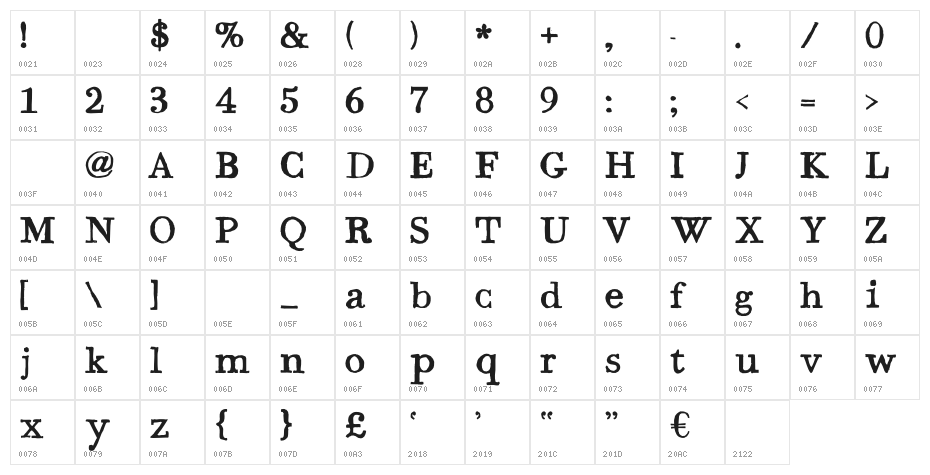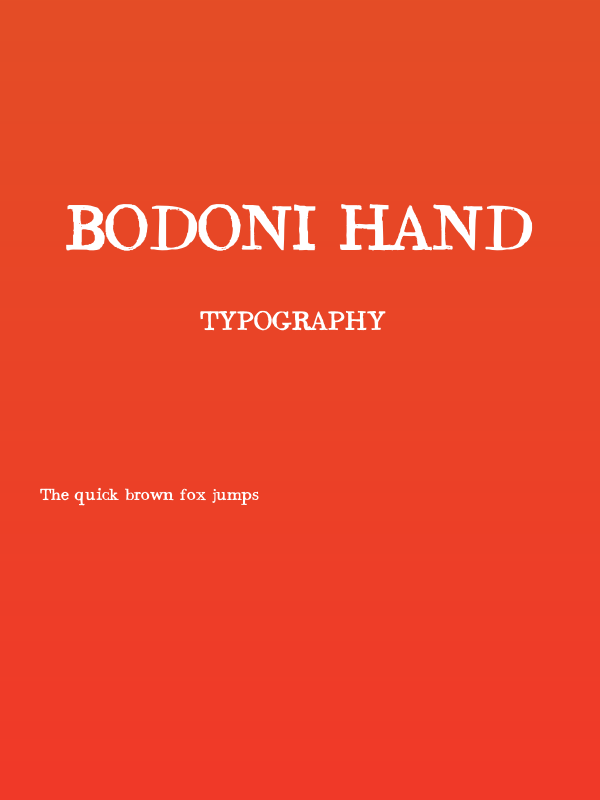
Bodoni Hand Font
✎ Distorted Eroded
| Kategorien | Distorted Eroded |
| Gesamtstil | Classic, Decorative |
| Vorgeschlagene Projekte | Ideal for projects requiring a classic yet artistic touch, such as book covers, posters, branding, and editorial design. |